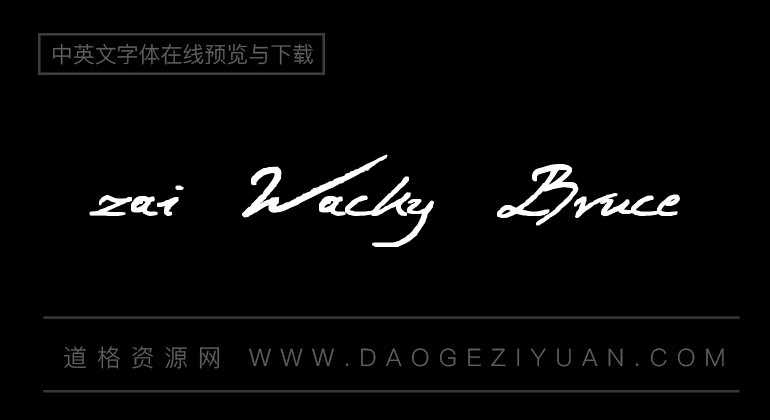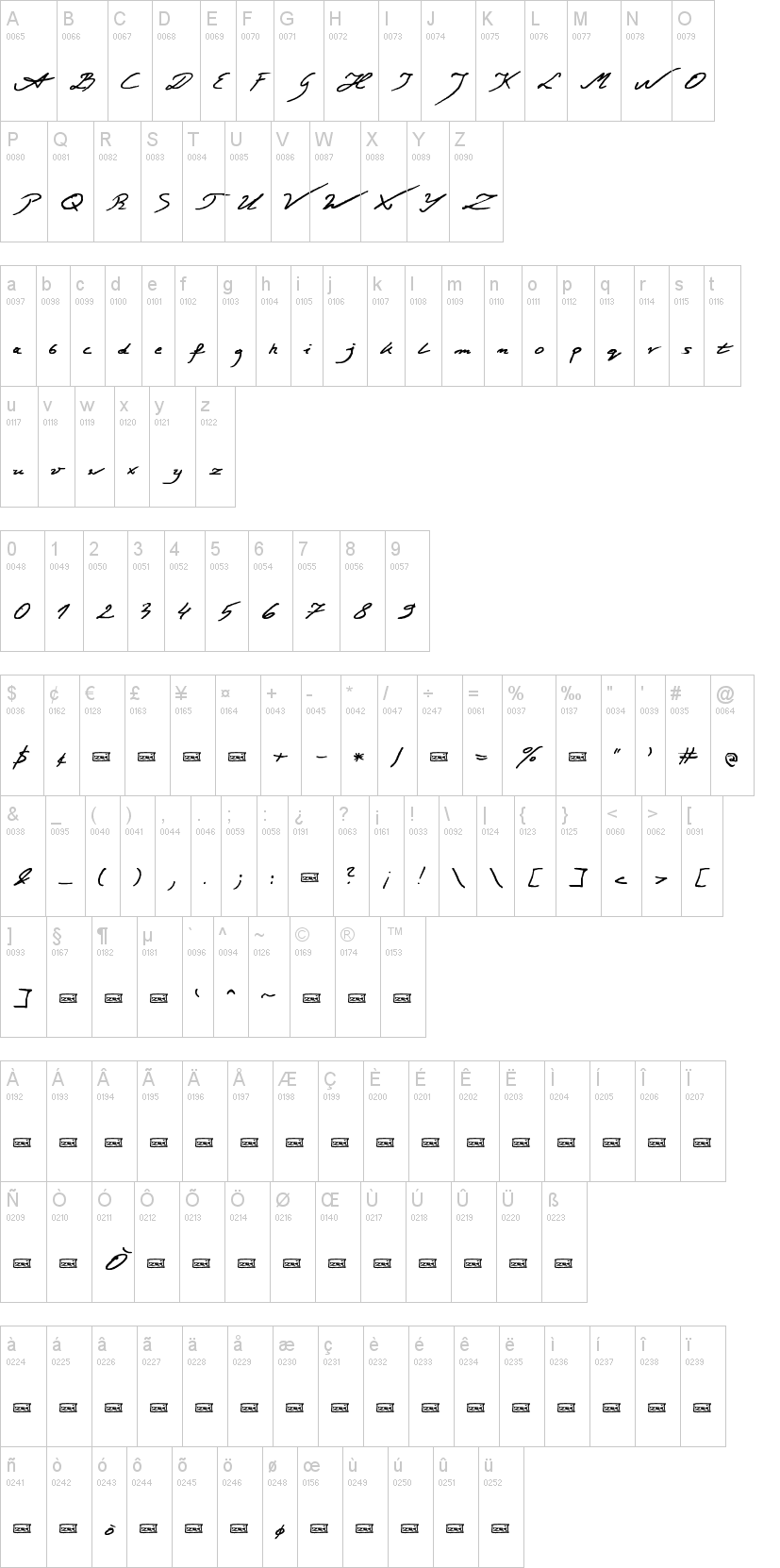
zai Wacky Bruce
Wacky Bruce 字体是一款由美国设计师Bruce Willen创作的手写体字体,它拥有流畅的线条和活泼的特点,充满了欢乐的气息。这款字体非常适合用于儿童类的设计,可以给设计师带来更多的创意空间,令设计更加有趣。Wacky Bruce 字体可以用于各种类型的设计,如海报、T恤、标志、卡片等,它可以让你的设计更加有趣,让你的作品更加生动。
zai Wacky Bruce是一款非常不错的手写艺术字体,具有很好的视觉感,适合于文化类的宣传设计、商业类品牌的广告和产品包装设计以及个性化文字排版等较多场景。
zai Wacky Bruce字符映射图